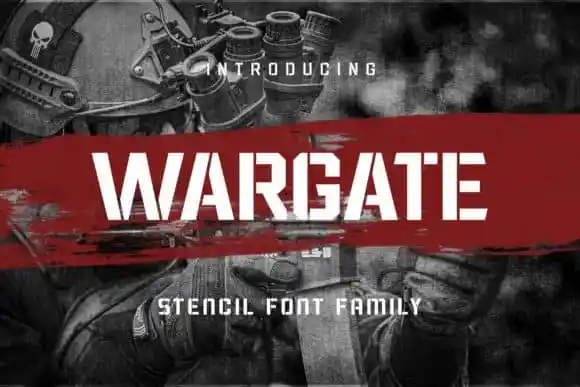
A Wargate Display Font é uma escolha perfeita para projetos que desejam se destacar no meio visual. Ela foi criada pelo designer Arterfak inspirado nos posters clássicos, oferecendo um tipo de display forte e grosso, inspirado nas designs militares e na grafitti urbana. Perfeito para quando você deseja garantir que seu projeto seja notado em uma galeria cheia de talentos. Com um estilo bold e com traços grossos, a Wargate Display Font é a escolha perfeita para quem busca dar vida aos seus projetos visuais, deixando-os inegavelmente chamativos. Ideal para logos, gráficos de site ou qualquer outro tipo de projeto visual que precise chamar atenção na multidão. Se você quer destacar-se, Wargate é definitivamente o fonte do futuro.